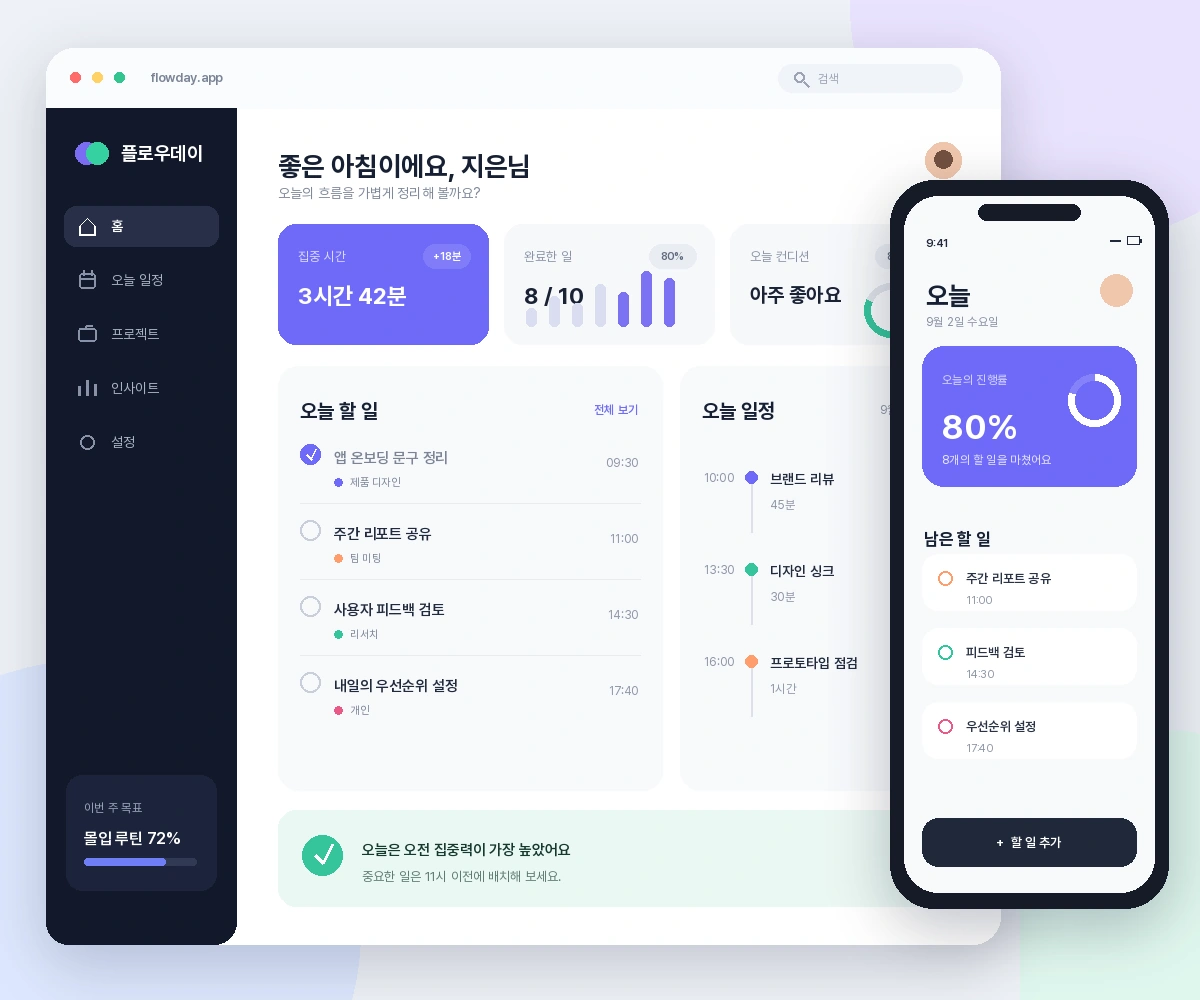
좋은 서체는 읽는 사람을 재촉하지 않습니다. 획이 고르면 눈이 문장을 따라가는 데 힘이 들지 않고, 그만큼 오래 읽어도 지치지 않습니다. 긴 글을 얹어 보고 끝까지 편안한지 확인해 보세요.
프리텐다드 — 추천 용도
- 인스타 · 카드뉴스 11위 — 간결한 네오 그로테스크 구조에 균형 잡힌 자형을 더한 현대적인 고딕체
- 문서 · 웹 본문 1위 — 9가지 굵기에 한글 11,172자를 모두 갖춘 화면용 고딕이라, 제목·본문·주석을 한 가족으로 나누고 웹폰트로도 자유롭게 씁니다.
- 리플렛 · 인쇄물 5위 — 간결한 네오 그로테스크 구조에 균형 잡힌 자형을 더한 현대적인 고딕체
- 쇼핑몰 상세페이지 15위 — 간결한 네오 그로테스크 구조에 균형 잡힌 자형을 더한 현대적인 고딕체